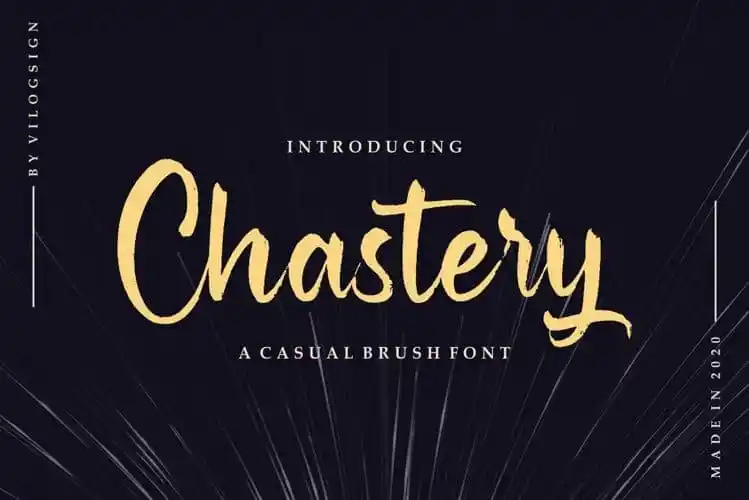
Chastery Brush Font – Download Grátis
A Chastery Brush Font é uma tipografia feita à mão que carrega consigo a essência da arte manual. Ela foi criada pelo Vilogsign e apresenta um estilo clássico, mas ainda manter sua amabilidade genuína. Este tipo de fonte é perfeitamente adequado para qualquer projeto de marca ou criação de logomarca. Além disso, ela faz parte da paleta ideal para invitações, cartões de aniversário e até mesmo itens relacionados à beleza. Seja por sua elegância clássica ou a sua simplicidade amigável, Chastery Brush Font é uma escolha ótima para designers em busca de um toque único que vai a fundo. Esta fonte é perfeita para aqueles que buscam uma combinação de sofisticação e simplicidade no seu design gráfico.